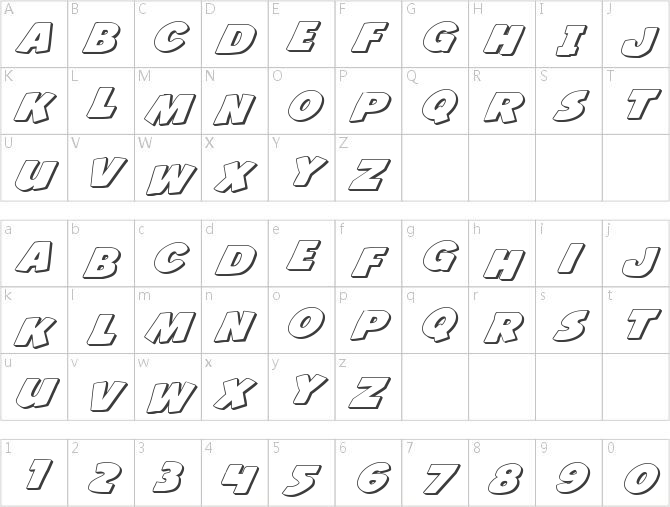
Jack's Candlestick 3D Expanded 詳情頁
Jack's Candlestick 3D Expanded字體字庫是一款讓人賞心悅目、百看不厭的英文字體,適合各類廣告和產(chǎn)品包裝設(shè)計(jì)應(yīng)用,字體大小0.14MB,格式為ttf字體,上傳用戶是@小咖,作者/版權(quán)方為未知